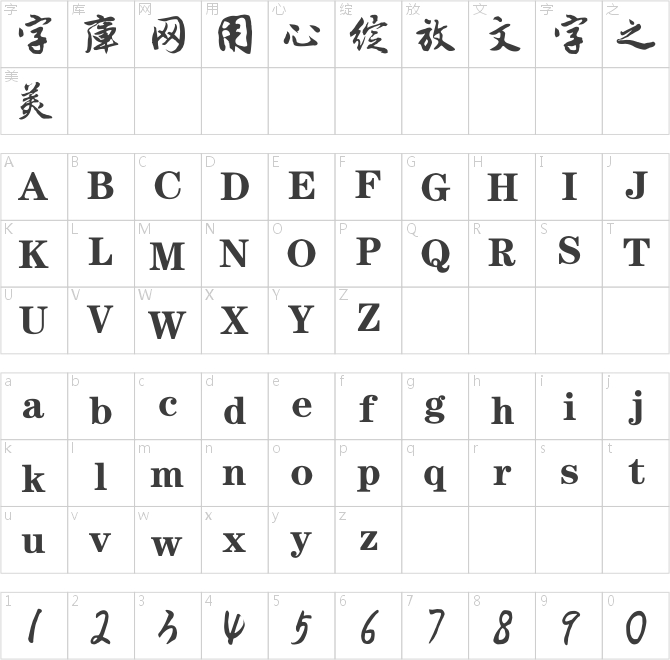
字體名稱: 逐浪唐寅行書體
逐浪唐寅行書體
逐浪唐寅行書體介紹
明代才子唐寅,字伯虎,其詩書畫俱佳,其中行書作品傳世頗多。
為此,逐浪字庫團隊專門整理,構建一套以唐寅行書為主體的書法字庫。
標準樣本:唐伯虎行書字帖《落花詩冊》。
1、橫線從左往右邊提
2、字體在原帖基礎上,注意絲連呼應,如“室”字。
3、按中華人民共和國簡體字法規為規范,當一個字遇到原帖為繁體時,則簡體相應部份也用繁體,避免生造字與原帖精神不符。
根據國家GB2312-80標準,涵括了常用的6763個字。
而逐浪出品,則包括現代常用字符、拉丁補充字符、生僻字符集,總庫達九千多個字符,匠心之作,方便設計、排版、出版、網店、印刷等各界行業使用。